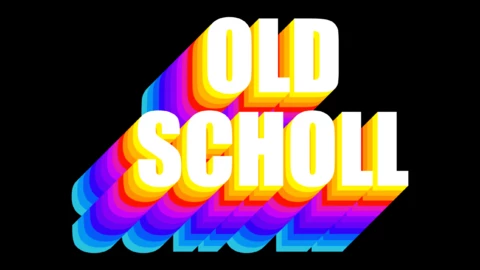
Старая школа Винтаж ретро 3d текст
Создание текстового эффекта "Roblox Font" Старая школа Винтаж ретро 3d текст с помощью нашего онлайн-генератора пользовательских шрифтов.